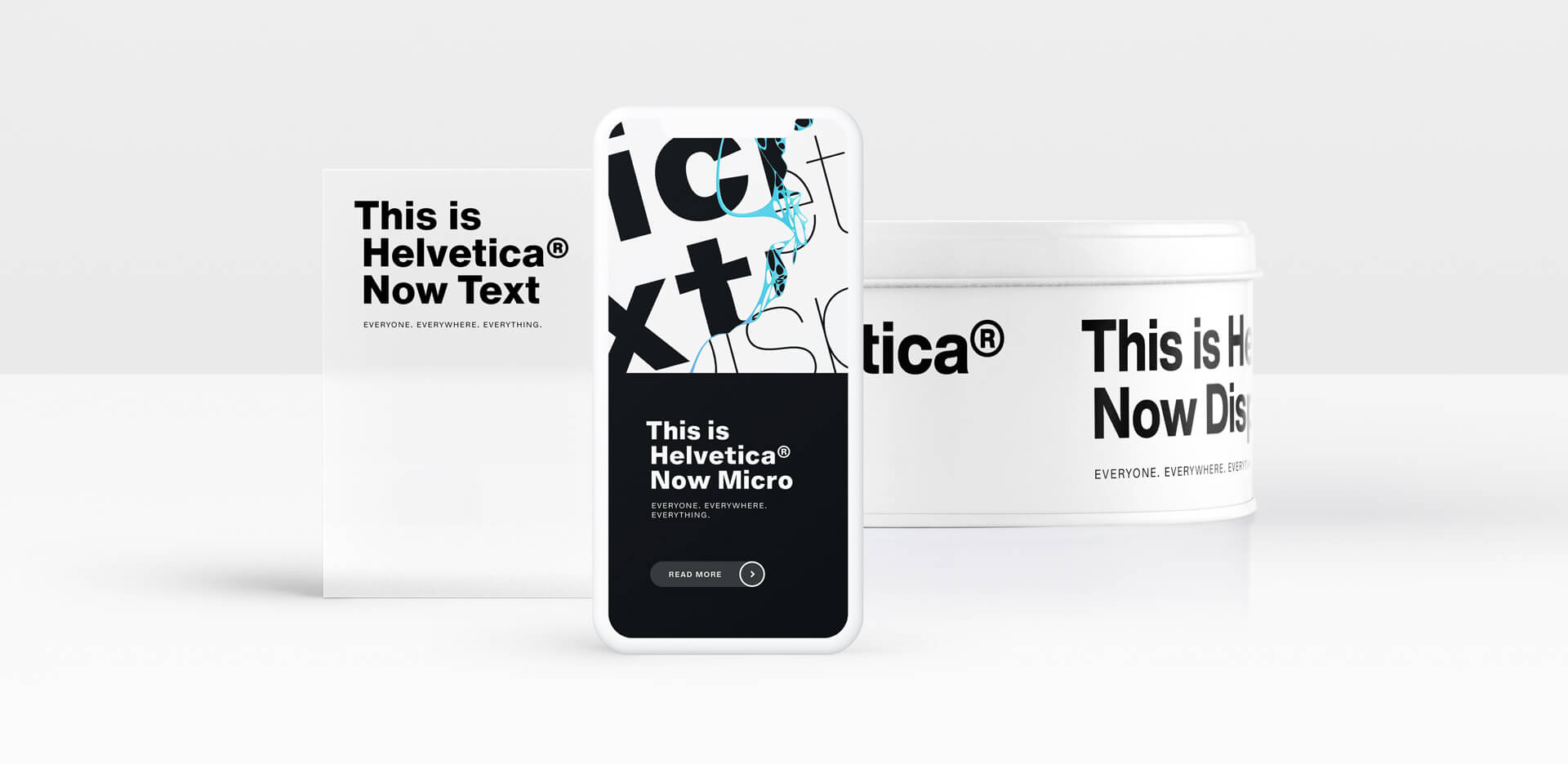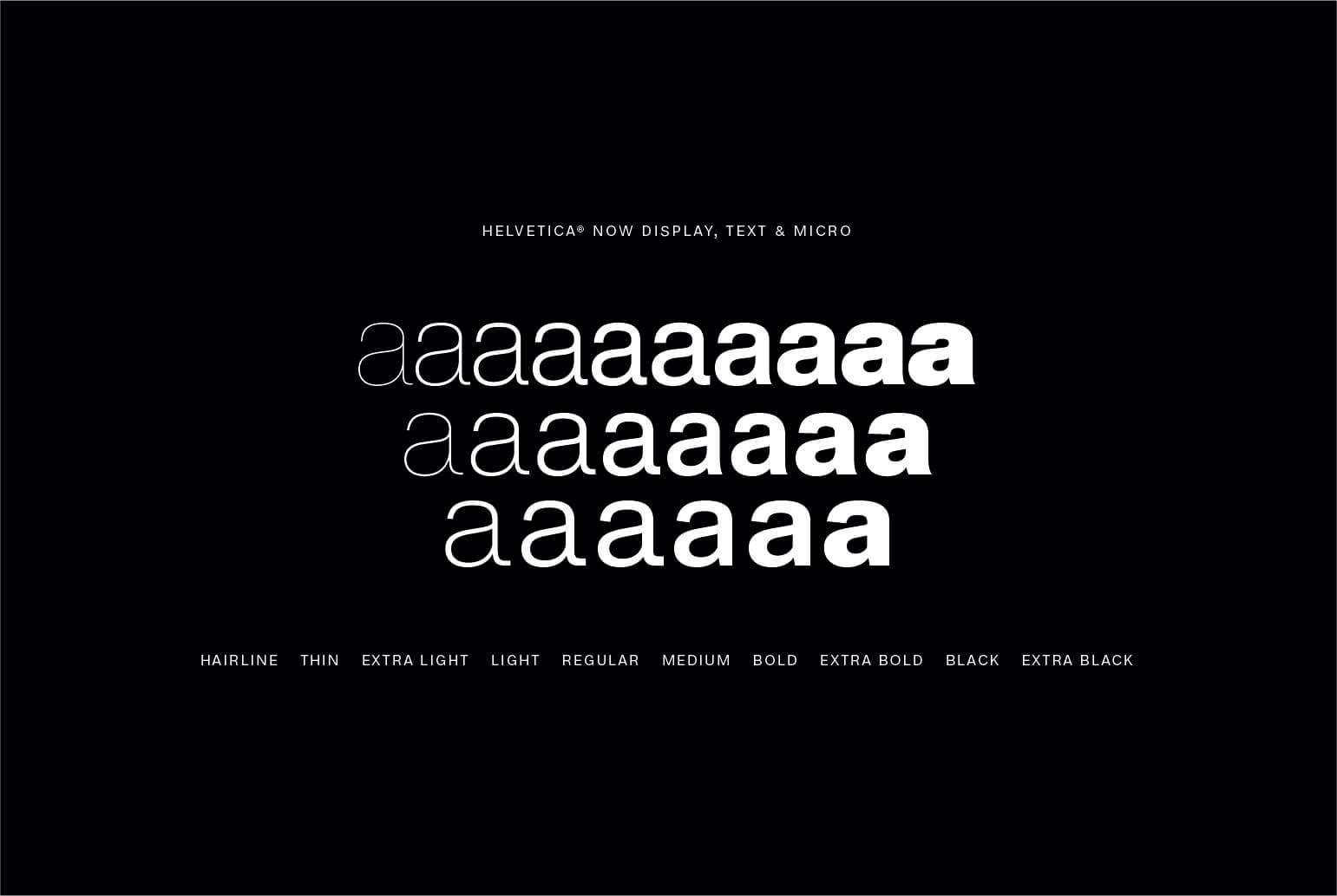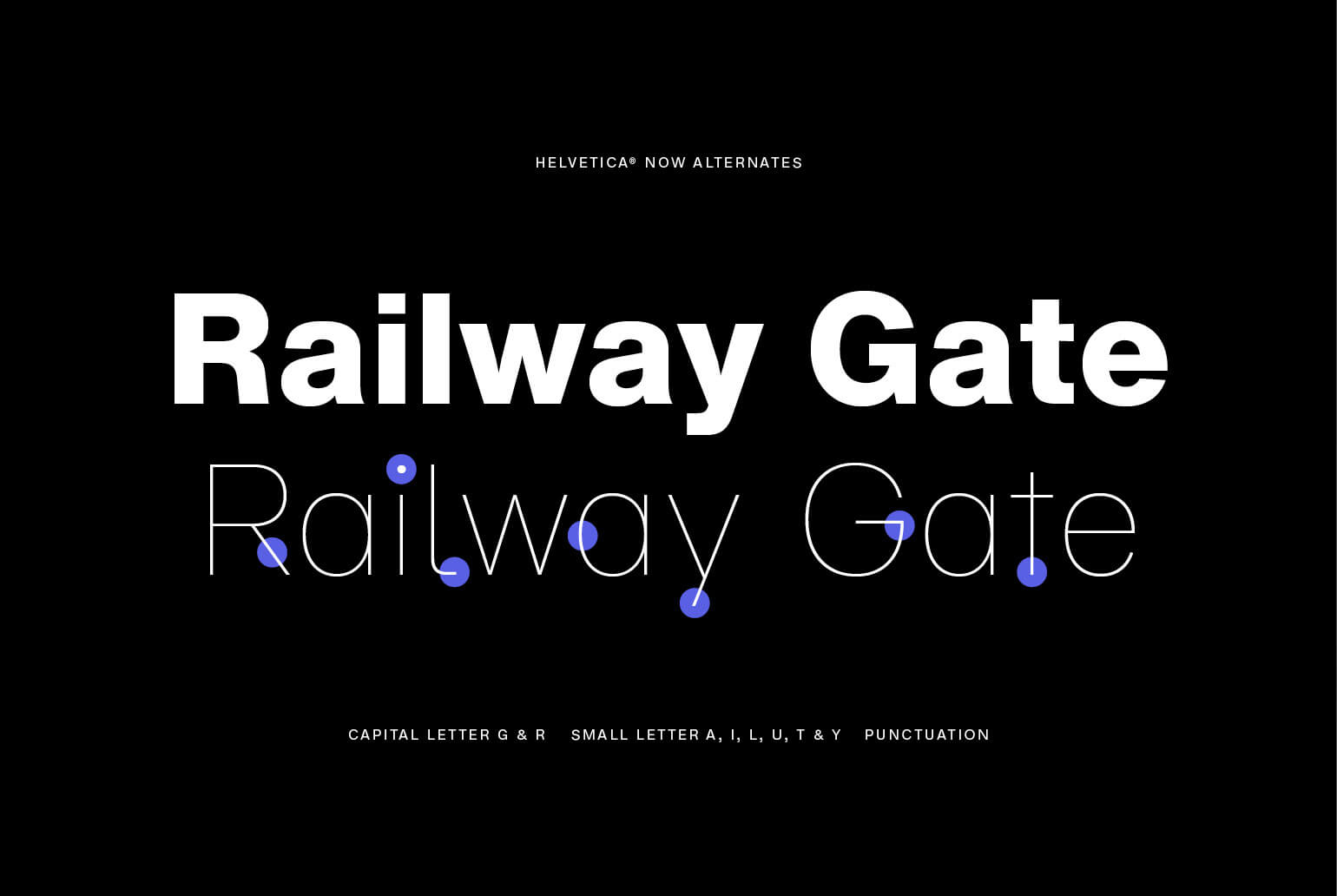
从Neue到Now:Helvetica如何在21世纪发展
自Helvetica®发布至今已有六十年,在此期间,字体仍然是清晰度和中立性的首选。但是,与许多字体一样,对它的要求也在增加。 Helvetica着名的瑞士简约现在预计将在不断增长的环境中以及比以往更广泛的尺寸范围内发挥作用。
设计师和工作室可能对1983年发布的NeueHelvetica®非常熟悉,但它是前数字时代的产物。
进入Helvetica®Now,精心重新构想这种经典字体,以解决现代品牌挑战,同时坚持其简约,清晰和全球吸引力的精神。以下是当前Neue用户可能想要切换的四个原因。
尺码
Helvetica Now提供微型,文本和显示尺寸,每种尺寸都针对特定环境量身定制 - 与Neue Helvetica不同,Neue Helvetica是用于文本类型绘制和间隔的。在海报上工作的设计师会发现Helvetica的清晰形状在更大的显示版本中得到了强调,这些版本在标题中间隔着头条新闻。它是Helvetica,但更加沉着和放心,用户更有可能尝试和表达自己。对于那些关注打印页面和运行副本的易读性的人来说,Helvetica Now的文字尺寸是一个主力,提供坚固的笔触和舒适的宽松间距。
“在海报上工作的设计师会发现Helvetica的清晰形状在更大的显示版本中得到了强调,这些版本在标题中间隔着头条新闻。
Micro版本是Helvetica Now的一个突出特点,它解决了Helvetica长期面临的一个问题 - 即微型挑战。虽然Neue Helvetica在微小尺寸上挣扎 - 例如在平板电脑和智能手表上 -  Helvetica Now的微型设计被简化和夸大。它们保留了小尺寸Helvetica的印象,并且它们的间距是松散的,这意味着在微观尺寸和低分辨率环境中保持易读性。
Helvetica Now提供微型,文本和显示尺寸,每种尺寸都针对特定环境量身定制 - 与Neue Helvetica不同,Neue Helvetica被绘制并间隔用于文本类型。
这三种尺寸的设计考虑了其最终环境,并进行了微调,以满足每种尺寸的要求。这意味着,与Neue Helvetica不同,设计师可以直接使用字体 - 无需额外的字距或印刷技巧。
调色板
Helvetica Now已被设计为一个完整的工具箱,允许字体更具表现力的一面出现。该系列提供了一整套可供选择的替代品,保持了设计的着名清晰度,但允许它根据需要采用微妙的不同声音。
设计师现在可以使用Helvetica Now的圆圈图,以及他们以前不得不从其他字体借用或单独创建的Helvetica风格箭头元素。这些额外功能包含在整个系列的每个重量和风格中,使Helvetica Now更有可能用于信息图形和标牌。
在整个范围内添加了替代形式的关键字形 - 如单层a。
细节
Helvetica Now不仅仅是刷新或更新。 Monotype的设计师团队回归原始设计,然后重新评估并重新绘制了系列中的每个字形,添加了多年来对字体进行的流行修改。重复出现的问题,例如容易混淆的资本I和小写字母l已经得到了解决,其中一个钩子版本可以提高较小尺寸的易读性。其他新增功能包括更新的@,圆形标点,圆角G,直腿R,单层a和小写u,没有尾随衬线。
“
Monotype的设计师团队多年来对字体进行了流行的修改。
虽然这些都使得Helvetica Now比其前辈更具实用性,但它也是对设计原始精神和精神的回归。 Monotype的设计团队在设计Helvetica Now时坚持严格的理念,为每一封信精心细化,以更加贴近字体的清晰,简洁和中立的口号。
“当你回到原始资源时,它更具可读性,与表格本身没有关系,只是间距,”Monotype Type Director Charles Nix说。 “这是关于研究字母之间的空间,弄清楚方法在早期是什么,它如何使类型更容易阅读,然后恢复它并改进它。”
这不是你所期望的
Helvetica可能是最着名的字体,因此设计唤起了设计师和最终用户的强烈感受。然而,Helvetica Now挑战了我们的观念。它秉承了设计的原始精神,但开辟了故事的新篇章。
熟悉Neue Helvetica的设计师会发现Helvetica Now是一个全新的前景 - 更大,更具表现力,并且用户有更大的实验潜力。它保留了原始人们非常喜爱的中立性,但也提供了寻找和采用新语调的机会。
“我想我们已经为Helvetica佳能推出了一个新的篇章,它将使它成为21世纪设计师手中的全新东西。我们已经仔细扩展了可能阻止其发展的严格遗产,“尼克斯说。